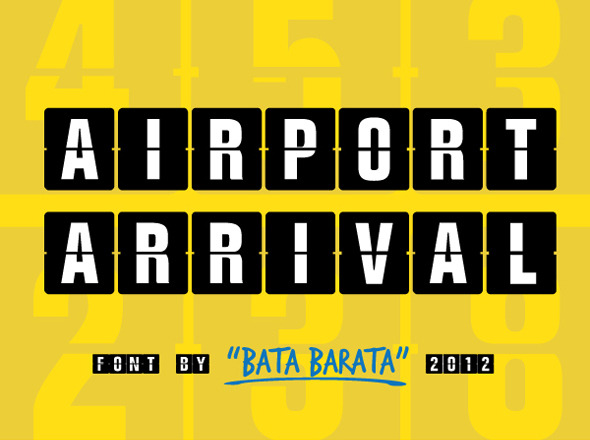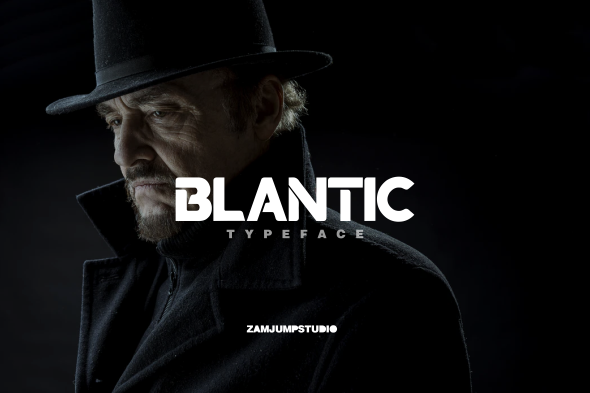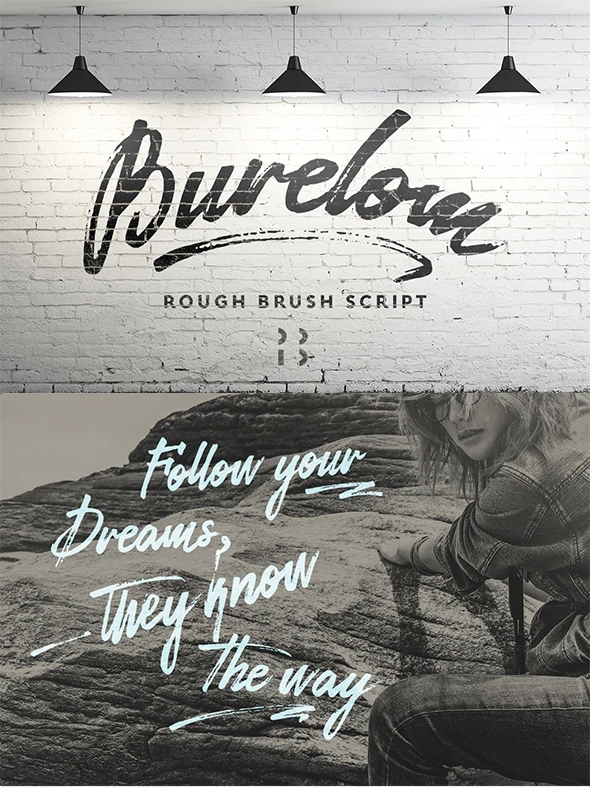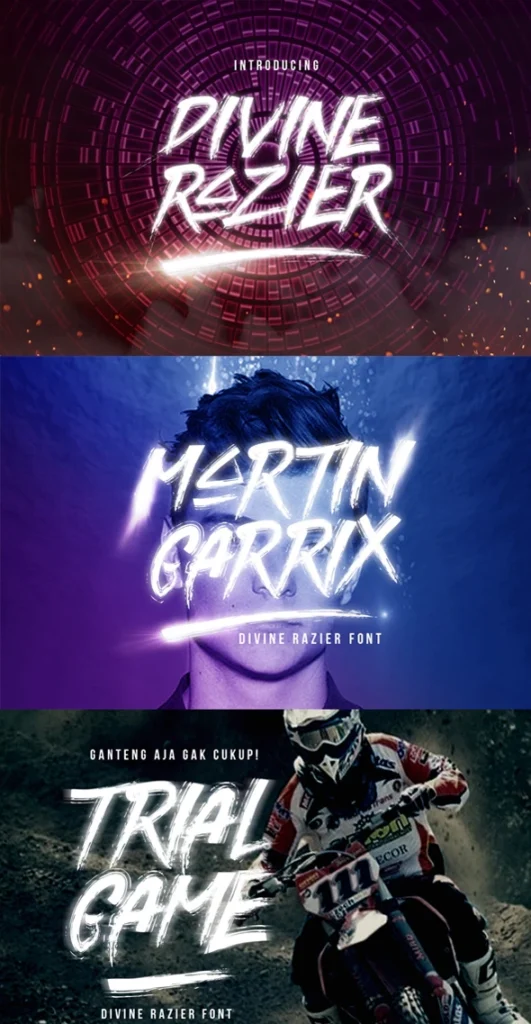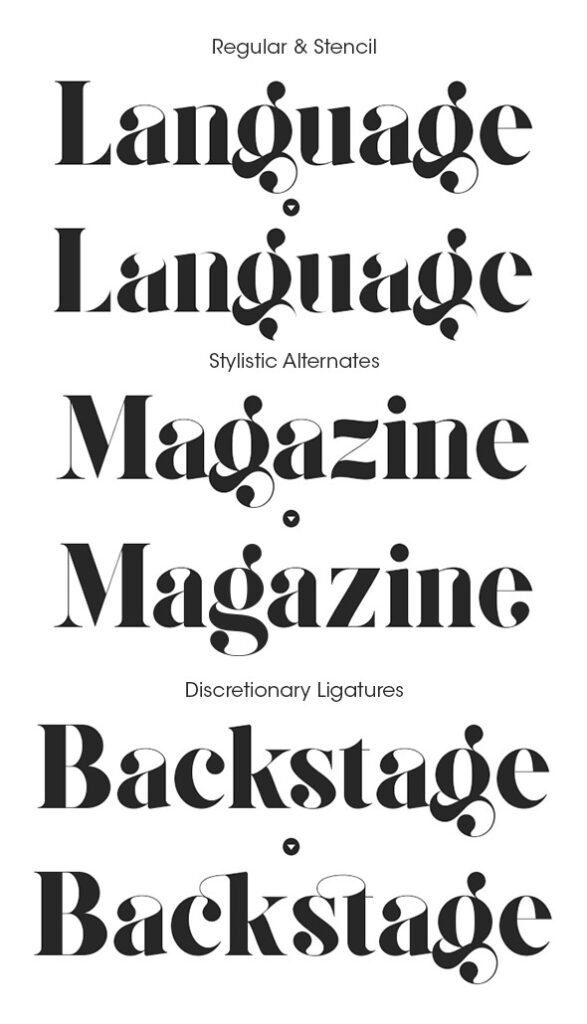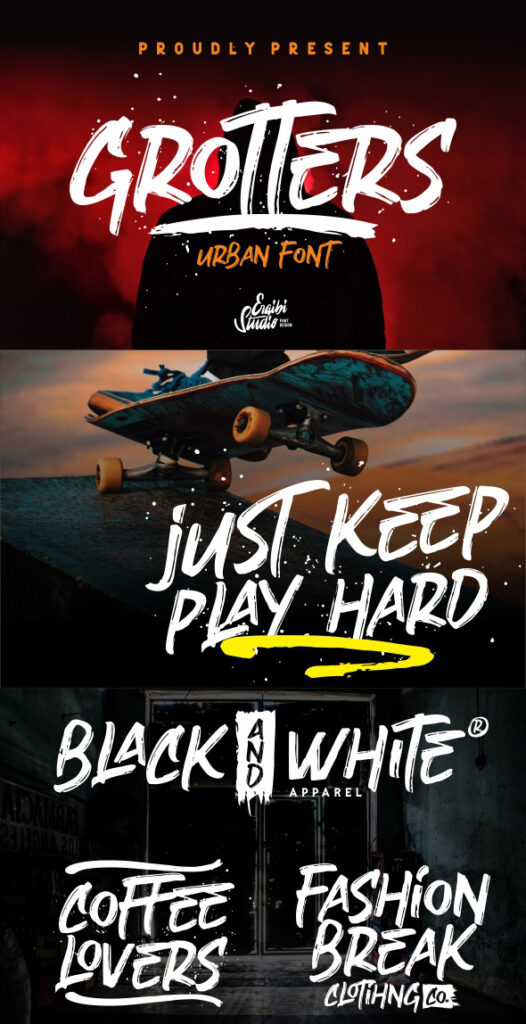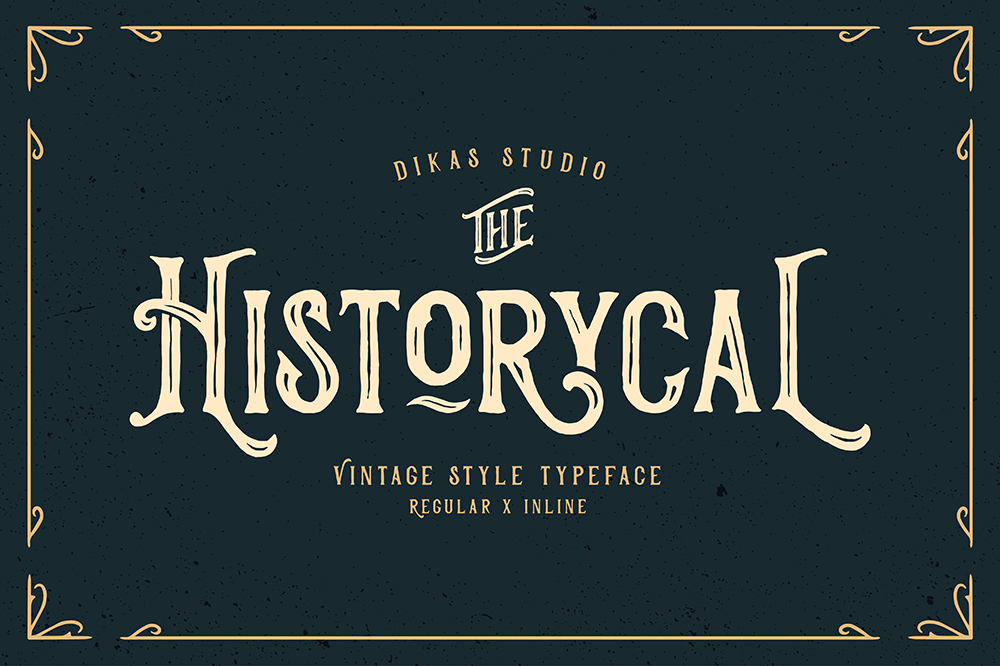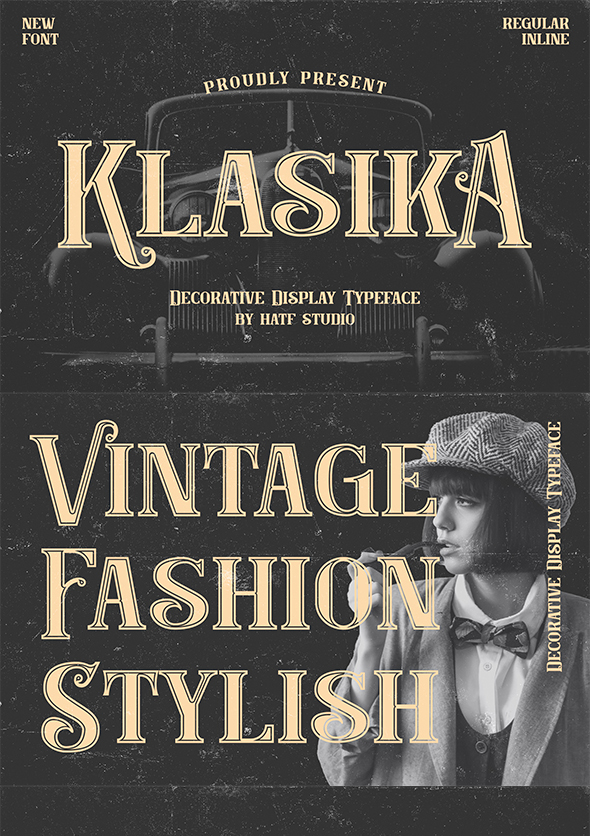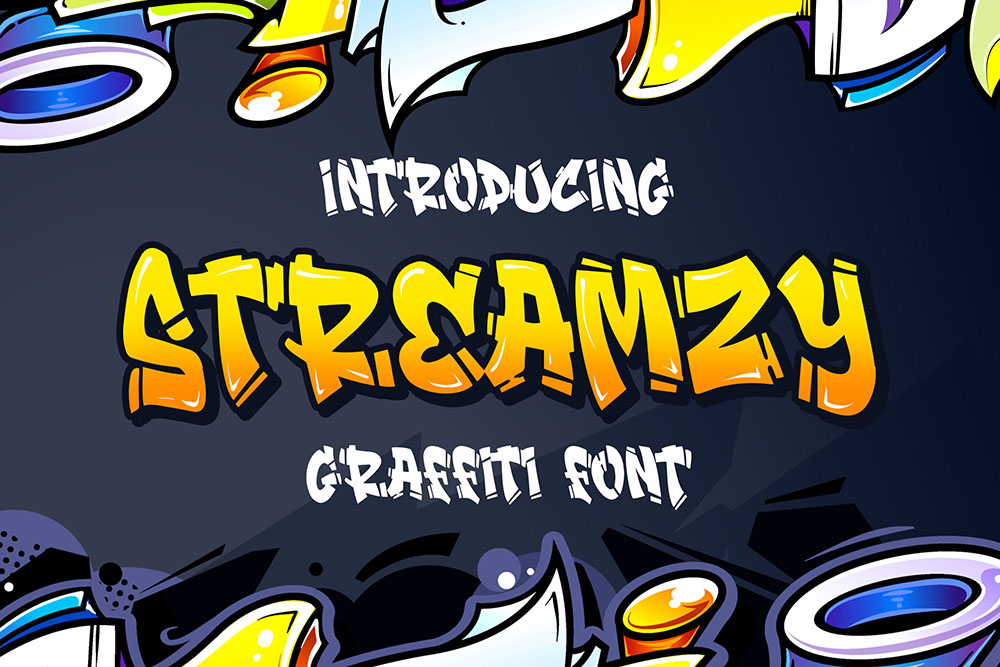
10 Fonts populares en graphicriver
Este mes Graphicriver trae muchas Fonts populares, escoge para compartir las más geniales y con gran estilo.
Ideales para gran variedad de proyectos publicitarios, identidad gráfica o marca personal.
The Rustic – 2 Style Font
By sigitdwipa
Airport Arrival
By Brandbusters
Divine Razier Font
By ovozdigital
Blantic
By zamjump
Burelom
By Naumtype
Streamzy – Graffiti Font
By Blankids
Klasika
By hatftype
Grotters
By ergibistudio
Historycal – 2 Font Styles
By DikasStudio
Giza Pro
By AnthonyJJames